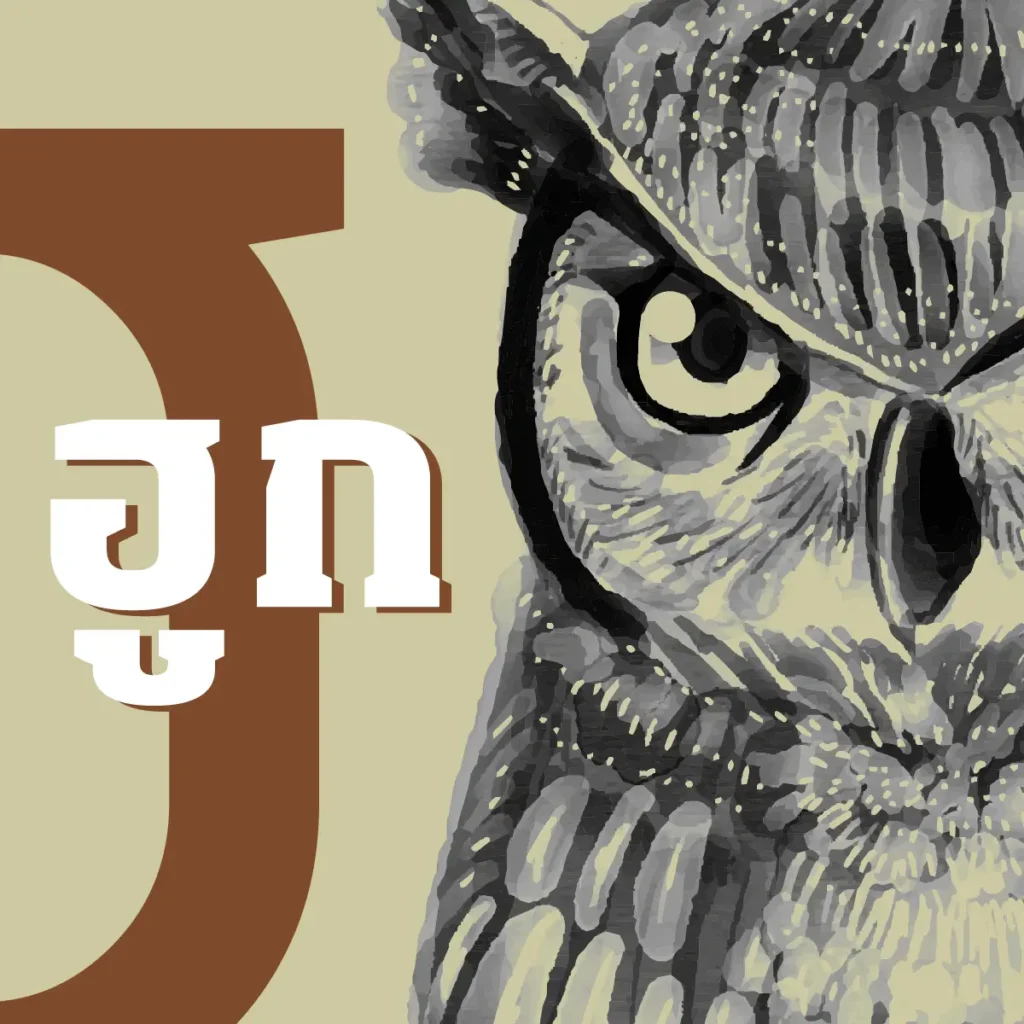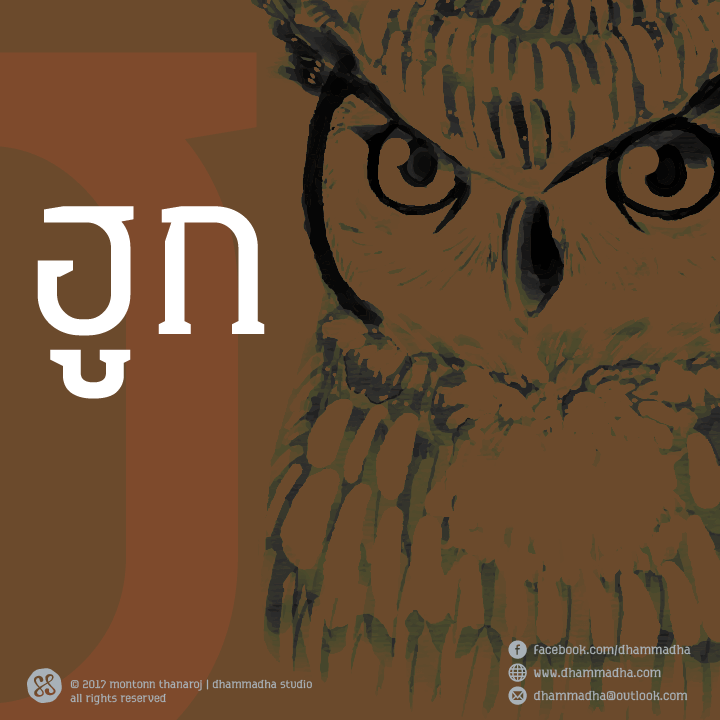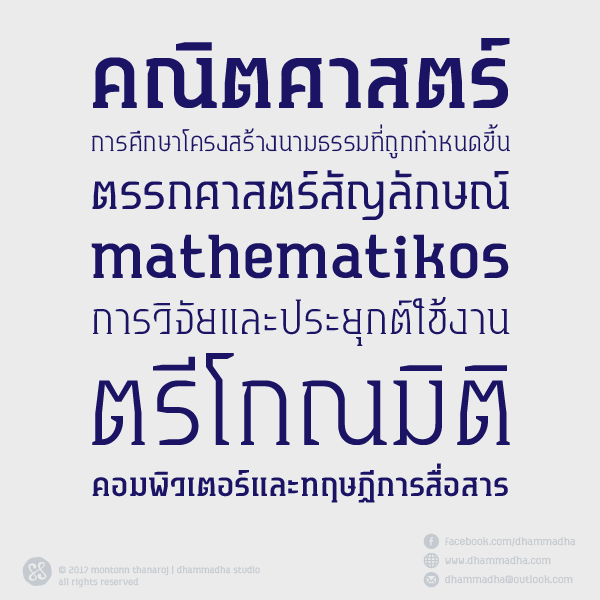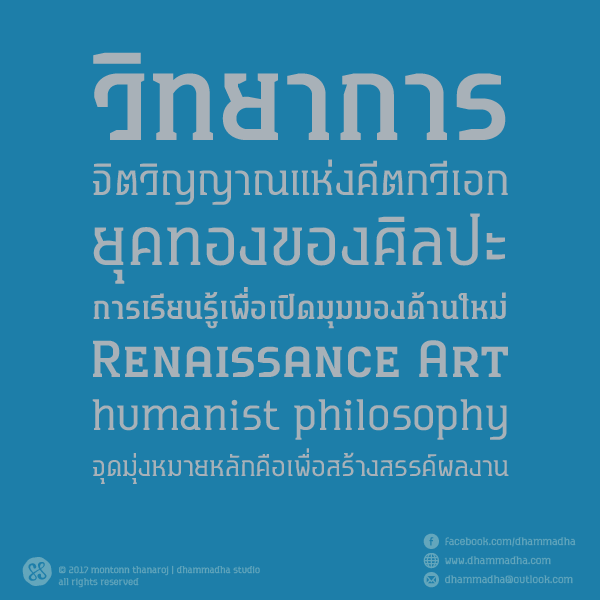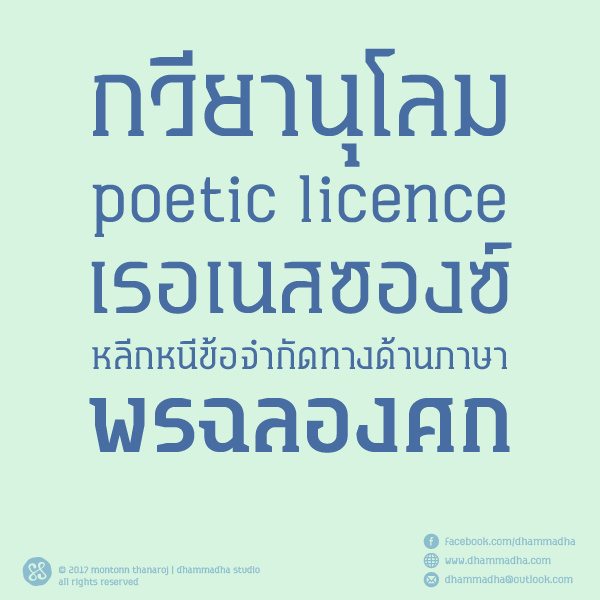
hook เป็นแบบร่างอักษร เมื่อครั้งผลิตงาน concept โดยนำอักษรไทยมาจัดวางสร้างสื่อภาพ และด้วยความบังเอิญ ฮูก ในการเขียนทับศัพท์ จะได้ความหมายที่แตกต่างออกไป ทำให้เกิดงานขึ้นมาอีกชิ้นหนึ่งความเป็นไปได้ที่เกิดขึ้น ทำให้เกิดแบบร่างชุดอักษรชุดนี้ขึ้นมา
ชุดอักษรประกอบด้วยฟอนต์ 5 น้ำหนัก พร้อมตัวเอียง
hook สามารถใช้งานภาษาไทยได้อย่างสมบูรณ์ ฟีเจอร์ใช้งานครอบคลุม